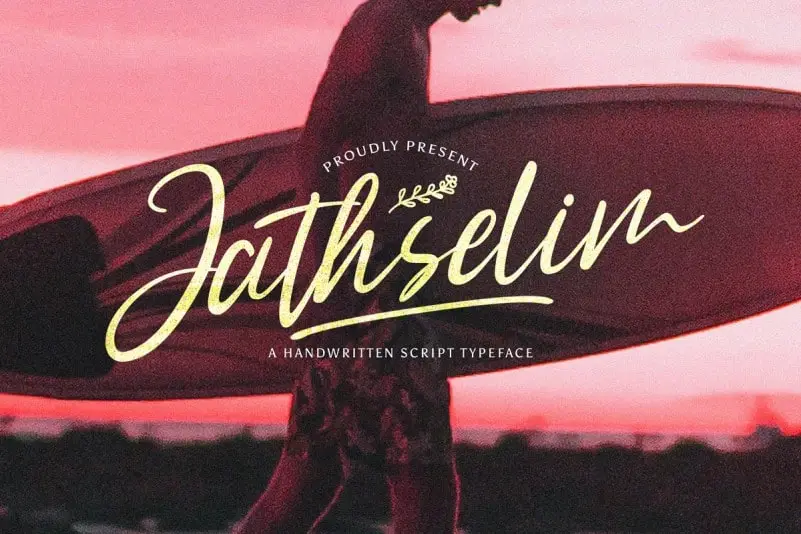
Jathselim Script Font é uma elegante tipografia cursiva que surgiu do talento criativo dos designers das StringLabs. Com seu estilo despojado e cheio de personalidade, essa fonte pode transformar qualquer projeto simples num verdadeiro marco de arte. Ela tem a propriedade perfeita de ser tanto uma escrita autêntica quanto um registro casual de pensamentos, tornando-a uma escolha ideal para designers que valorizam a criatividade e buscam adicionar um toque único aos seus projetos. O Jathselim Script Font é tão versátil que se adapta perfeitamente a uma ampla variedade de designs. Seja para títulos chamativos, desenhos detalhados ou até mesmo ilustrações, ele oferece uma combinação harmônica e única de elegância e originalidade. Com Jathselim Script Font, você pode explorar novas ideias e fazer com que os seus projetos ganhem vida através dos traços fluidos e expressivos desta fonte singular. Jathselim Script Font é perfeito para aqueles designers em busca de algo mais que uma simples tipografia formal. Ele traz a personalidade e o charme da escrita manual, tornando cada projeto único e memorável. Adicionar Jathselim Script Font aos seus trabalhos é como adicionar um elemento autêntico à sua obra, permitindo-lhe expressar-se de maneira única enquanto mantém uma harmonia perfeita entre texto e design.